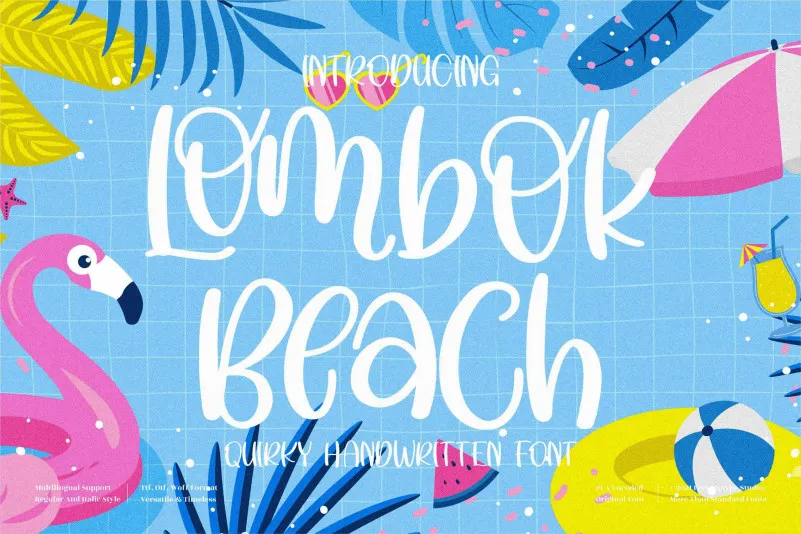
Lombok Beach Font – Fonte Grátis
Lombok Beach Font
Esta é uma fonte divertida, alegre, quirk e redonda criada à mão. Perfeita para agregar um toque agradável às criações que exigem um toque emocionante. Lombok Beach Font foi projetada pelo designer perspectype na categoria de Playful Fonts. Essa escolha da fonte trará uma personalidade especial ao seu design, tornando-o ainda mais atraente e envolvente. Seja em cartazes de shows musicais, embalagens para produtos ou até mesmo no layout do site de um novo negócio de surf: Lombok Beach Font adicionará aquele toque especial que faz sua marca brilhar. Aproveite para criar algo único com essa font encantadora e divertida.